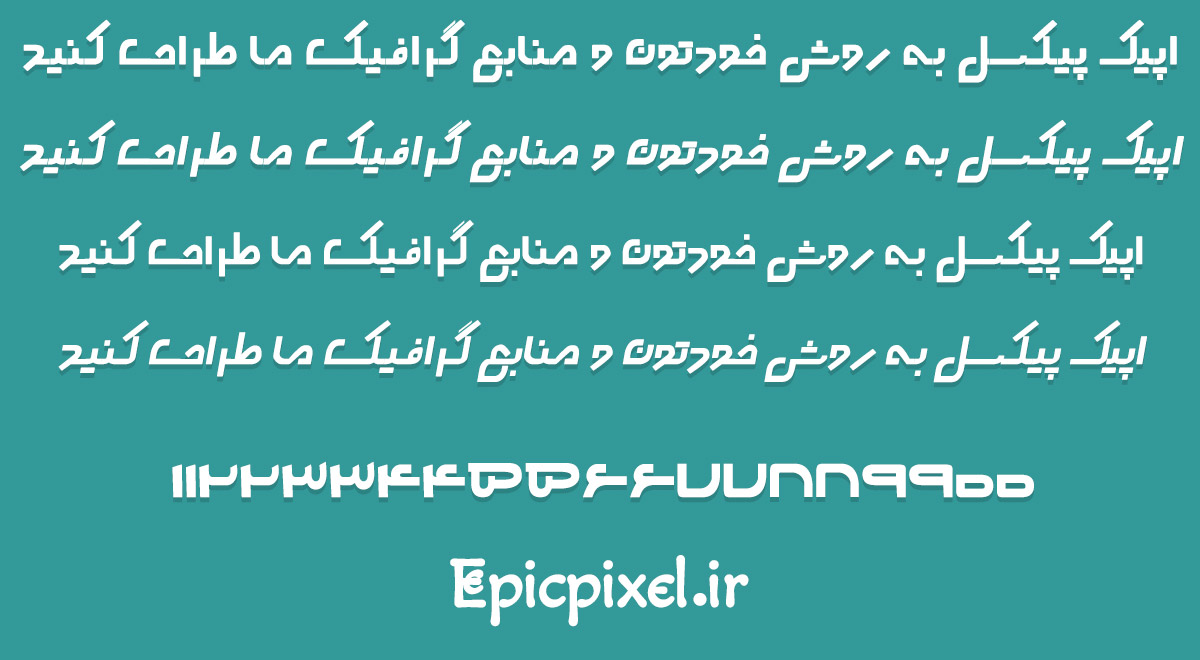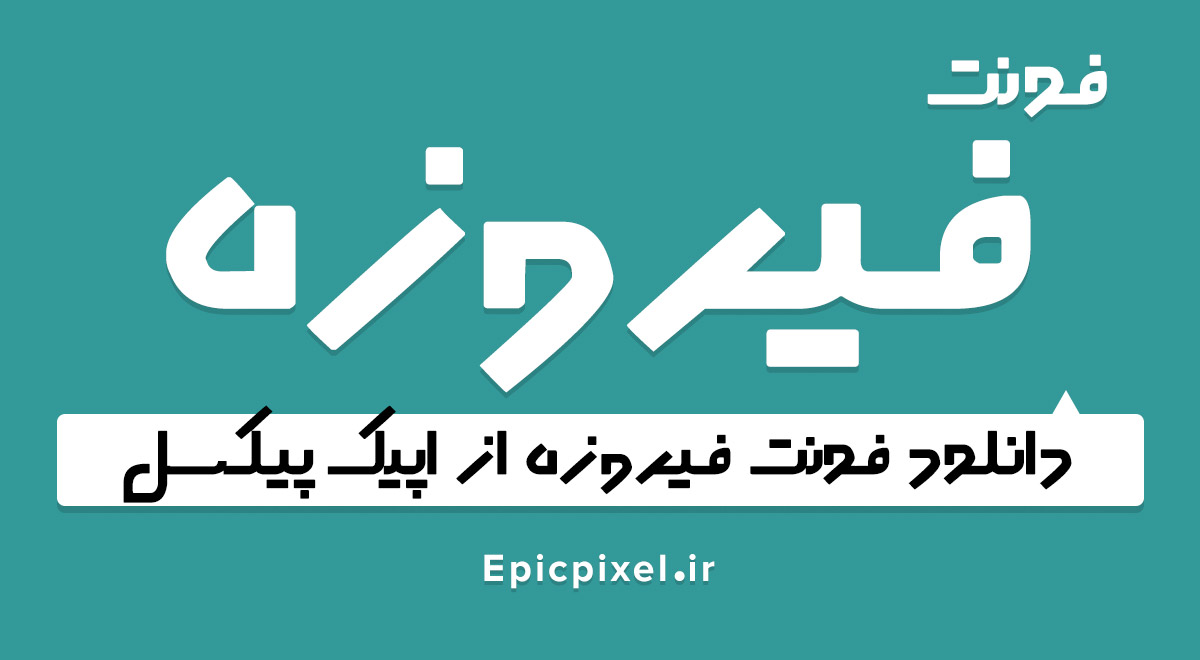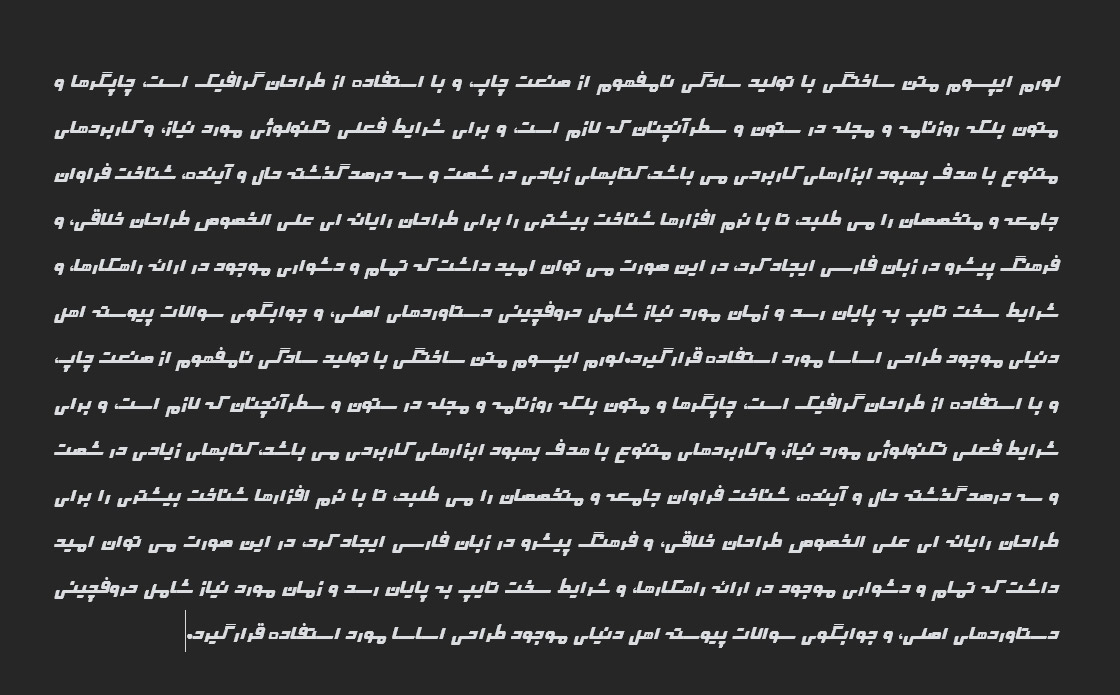
فونت فیروزه زیبایی ناب در دنیای نوشتار
در دنیای طراحی گرافیک، فونت ها نقشی اساسی ایفا می کنند. آنها مانند رنگ ها و تصاویر، می توانند احساسات و حالات مختلف را منتقل کنند و به محتوای شما شخصیت و هویت بخشند. یکی از فونت های زیبا و با اصالت در زبان فارسی، فونت فیروزه است. این فونت با زیبایی و ظرافت خود، می تواند در طراحی انواع مختلف گرافیک استفاده شود، از جمله طراحی وب سایت و اپلیکیشن، طراحی لوگو و کارت ویزیت، و طراحی پوستر و بروشور.
تاریخچه فونت فیروزه
فونت فیروزه توسط طراحان ایرانی در سال 1385 طراحی شده است. این فونت بر اساس فونت فارسی شکسته طراحی شده است، اما با ظرافت و زیبایی بیشتری. فونت فیروزه در دو وزن نازک و معمولی منتشر شده است.
ویژگی های فونت فیروزه
فونت فیروزه دارای ویژگی های منحصر به فردی است که آن را از سایر فونت های فارسی متمایز می کند. این فونت:
زیبا و با اصالت است.
خوانا و قابل فهم است.
وزن نازک آن برای متن های با اندازه کوچک مناسب است.
وزن معمولی آن برای متن های با اندازه متوسط مناسب است.
برای طراحی انواع مختلف گرافیک قابل استفاده است.
کاربردهای فونت فیروزه
فونت فیروزه می تواند در طراحی انواع مختلف گرافیک استفاده شود، از جمله:
طراحی وب سایت و اپلیکیشن
طراحی لوگو و کارت ویزیت
طراحی پوستر و بروشور
طراحی صفحات اجتماعی
طراحی تبلیغات چاپی
دانلودمزایا استفاده از فونت فیروزه
استفاده از فونت فیروزه مزایای بسیاری دارد، از جمله:
می تواند به محتوای شما شخصیت و هویت بخشد.
می تواند احساسات و حالات مختلف را منتقل کند.
باعث جذابیت بیشتر محتوای شما می شود.
باعث خوانایی بهتر محتوای شما می شود.
می تواند به برند شما کمک کند تا متمایز شود.
جمع بندی
فونت فیروزه یکی از زیباترین و با اصالت ترین فونت های فارسی است. این فونت می تواند در طراحی انواع مختلف گرافیک استفاده شود و باعث زیبایی و جذابیت بیشتر محتوای شما شود. اگر به دنبال یک فونت با کیفیت و زیبا برای طراحی گرافیک خود هستید، فونت فیروزه یکی از بهترین گزینه های شما است.
آیا فونت فیروزه از نظر خوانایی مشکلی دارد؟
خیر، فونت فیروزه از نظر خوانایی بسیار خوب است و در اندازه های مختلف قابل استفاده است.